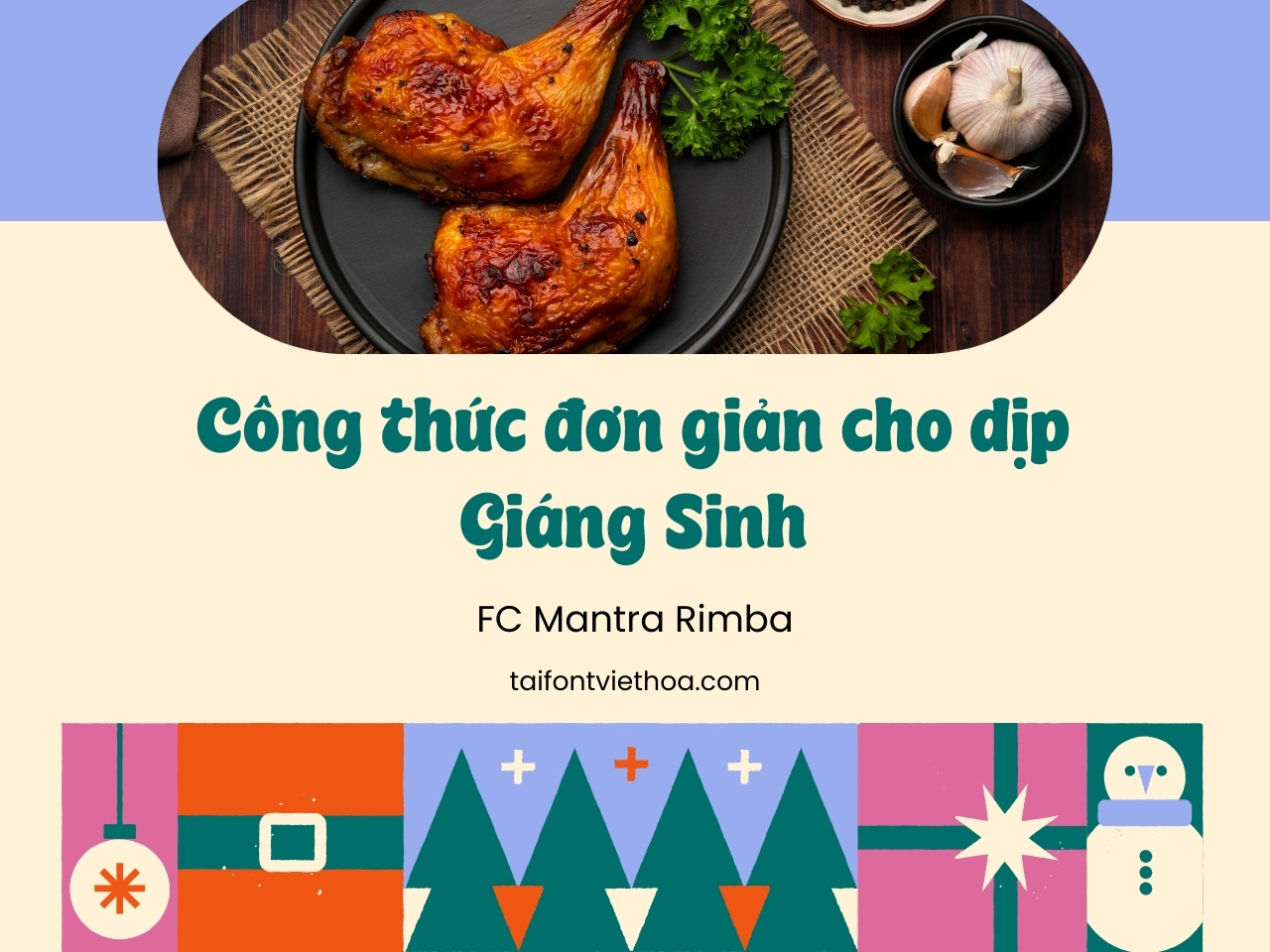
Giới thiệu về font Mantra Rimba và phiên bản Việt hóa
FC Mantra Rimba là phiên bản Việt hóa từ font gốc “Mantra Rimba” – một thiết kế độc quyền của Zain Fahroni, nhà thiết kế đến từ Indonesia. Font được phát hành trên nhiều nền tảng thiết kế quốc tế như Creative Market, Fontbundles, nổi bật nhờ tinh thần bản địa mạnh mẽ và nét đẹp tự nhiên nguyên bản. Với phong cách hiển thị (display font) cá tính, Mantra Rimba mang đến cảm giác hoang dã, tự do và đầy chất nghệ thuật thủ công. Font gốc hỗ trợ hơn 60 ngôn ngữ sử dụng bảng chữ cái Latin, rất phù hợp trong các thiết kế toàn cầu.
Phiên bản Việt hóa do cộng đồng Font Chuẩn thực hiện đã tối ưu hóa bảng ký tự để hiển thị hoàn chỉnh tiếng Việt, giữ nguyên tinh thần thiết kế mộc mạc và đặc trưng ban đầu. Font này được taifontviethoa.com chọn lọc, kiểm duyệt và chia sẻ, nhằm phục vụ các nhà thiết kế cần một phông chữ đậm tính nghệ thuật, mang âm hưởng văn hóa Á Đông kết hợp phong cách hiện đại. Đây là lựa chọn không thể thiếu trong các dự án sáng tạo đề cao sự cá tính và bản sắc riêng biệt.
Đặc điểm thiết kế và ứng dụng thực tiễn
FC Mantra Rimba mang kiểu dáng chữ hiển thị (display font) kết hợp giữa yếu tố thủ công và thiên nhiên. Các ký tự được vẽ bằng tay, với phần đầu và nét nối hơi thô ráp nhưng đầy cá tính, gợi liên tưởng đến cọ vẽ hoặc chất liệu gỗ khắc. Tỉ lệ chữ được xử lý tự do, mang lại sự bất quy tắc thú vị giúp thiết kế trở nên độc đáo và bắt mắt.
Font này rất phù hợp với các thiết kế logo, tiêu đề poster lễ hội, menu nhà hàng ẩm thực, nhãn bao bì thủ công, hoặc các sản phẩm mang phong cách bản địa, dân gian. Ngoài ra, FC Mantra Rimba còn phù hợp trong ngành truyền thông, bất động sản, thiết kế bảng hiệu hoặc các dự án sáng tạo dành cho mùa lễ hội, trung thu, sinh nhật hoặc sản phẩm theo chủ đề văn hóa.